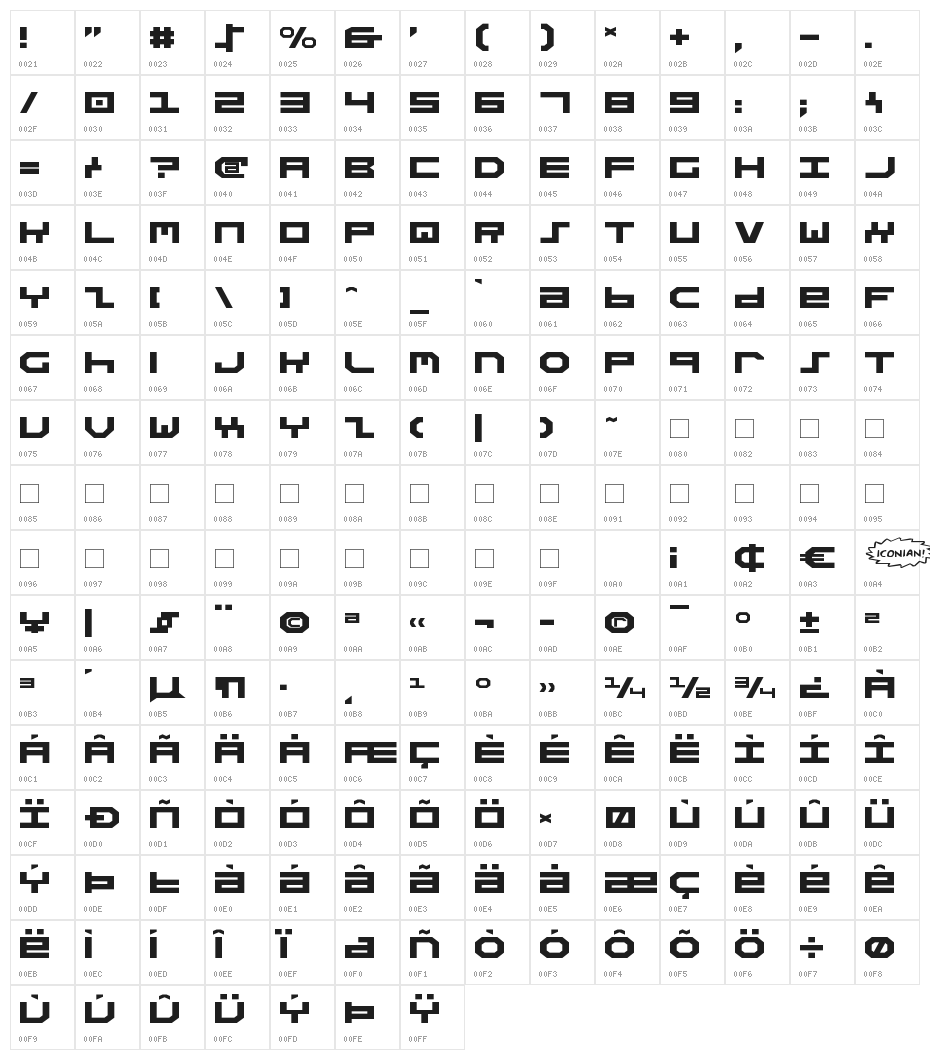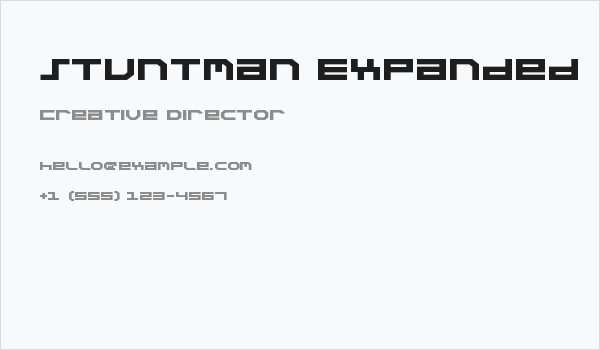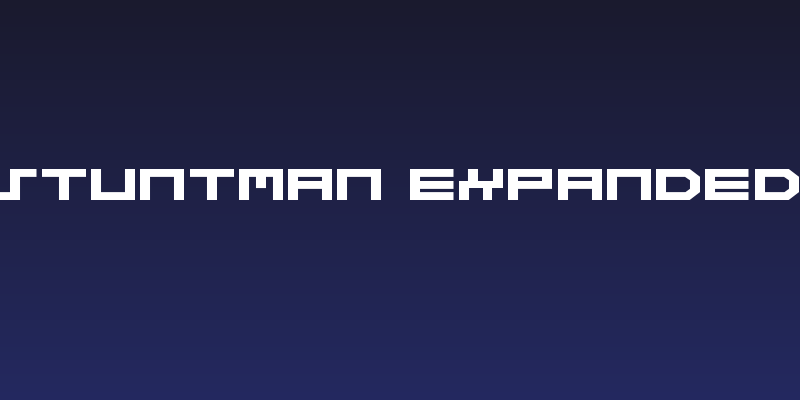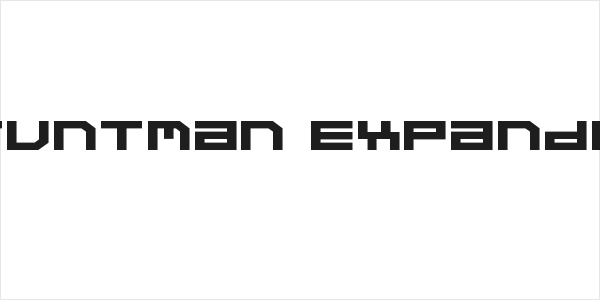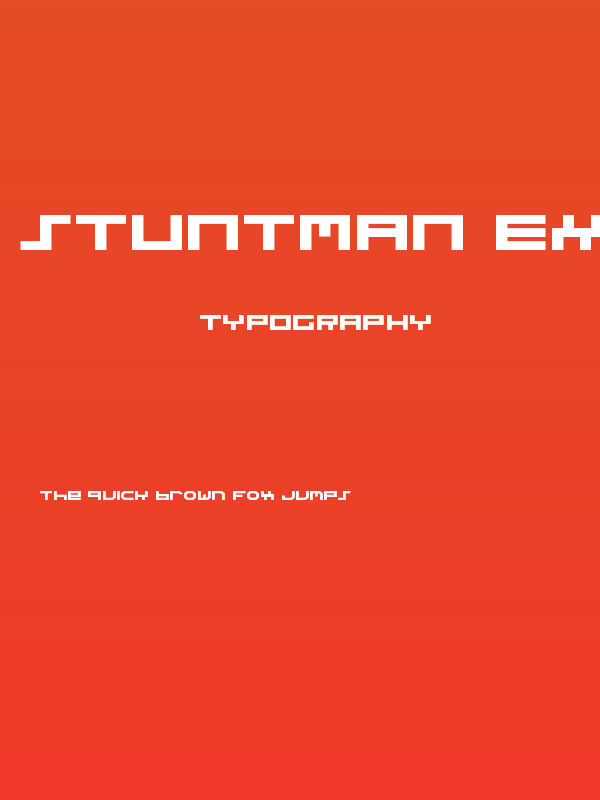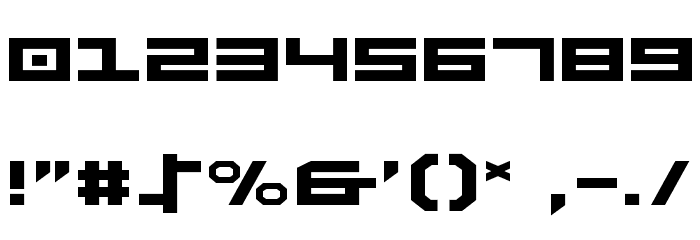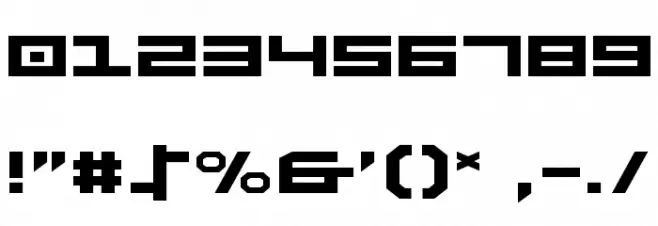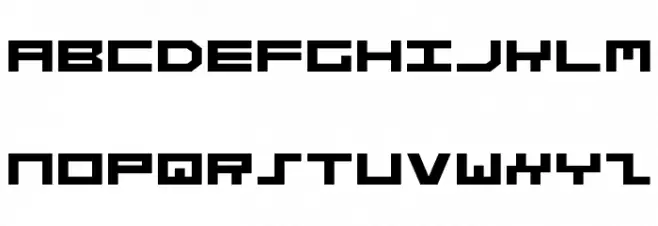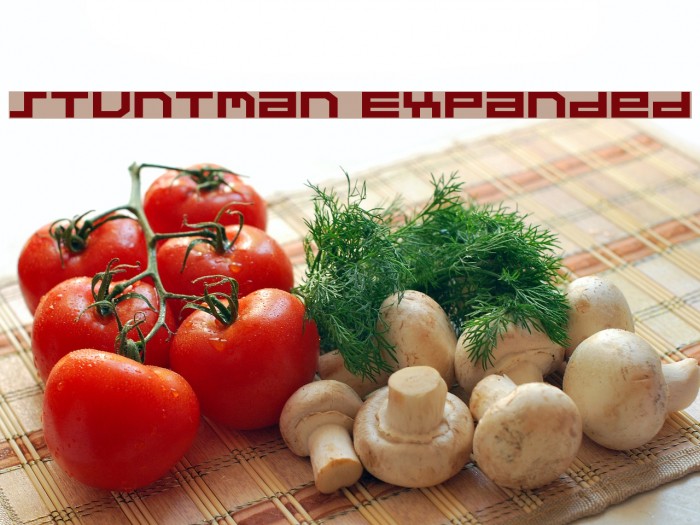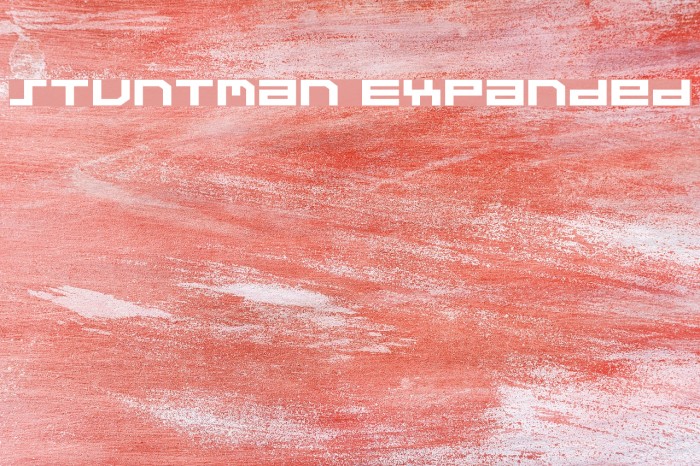
Stuntman Expanded Font
| Projets proposés | Ideal for sci-fi themed designs, video game titles, posters, and branding that requires a modern, digital aesthetic. |